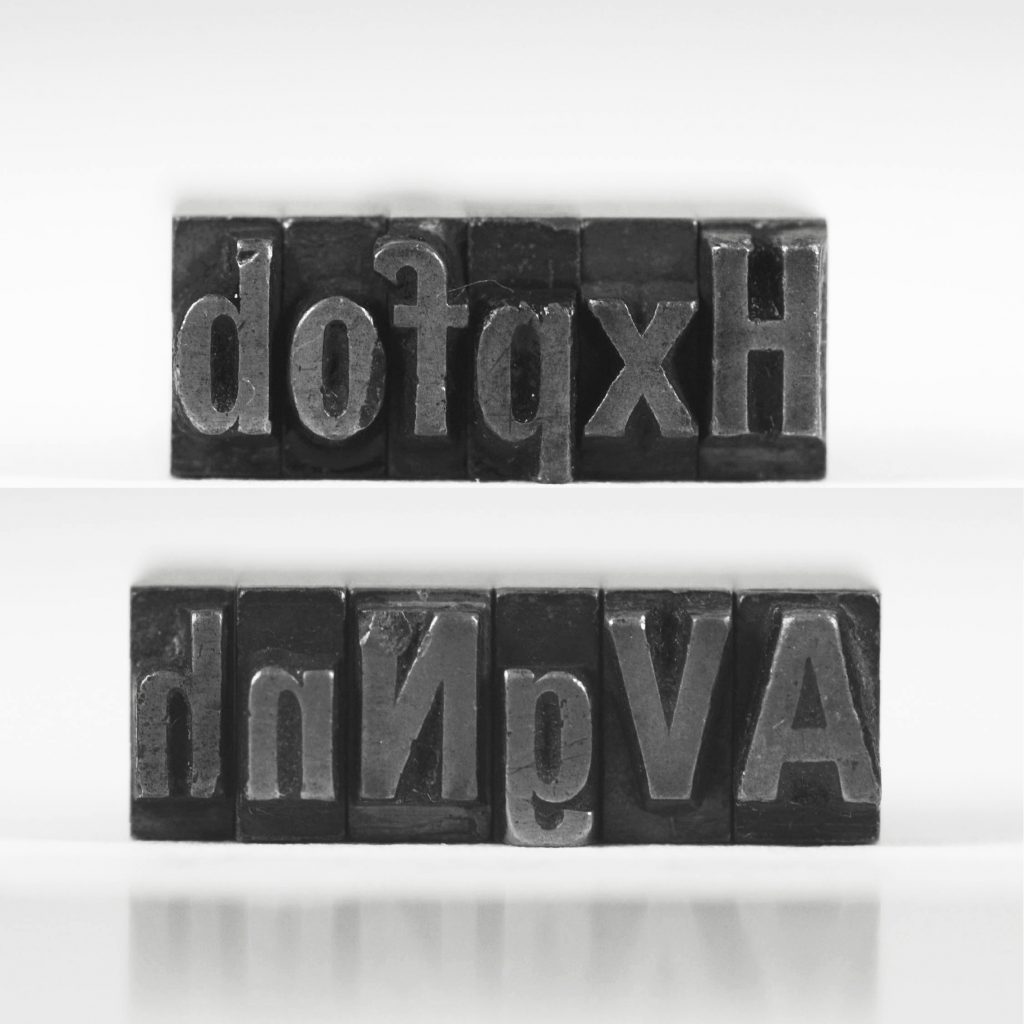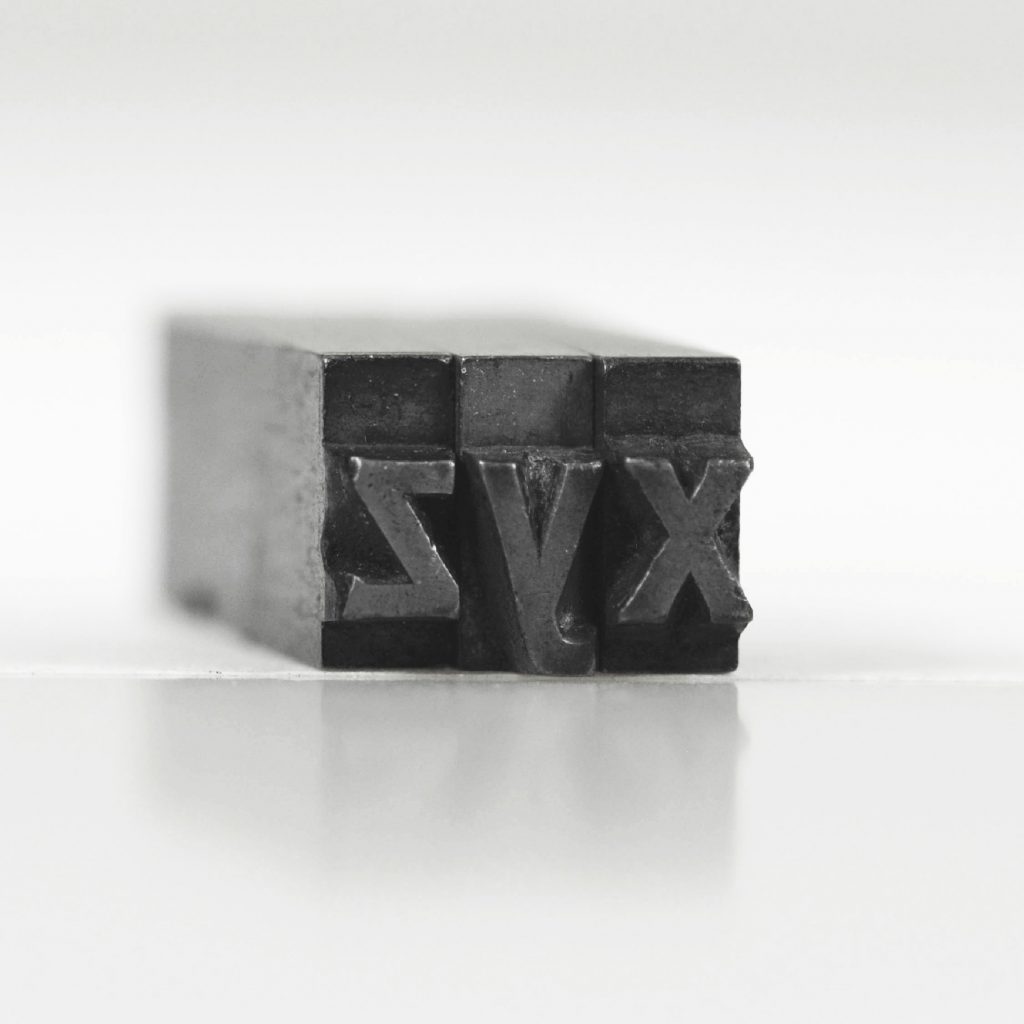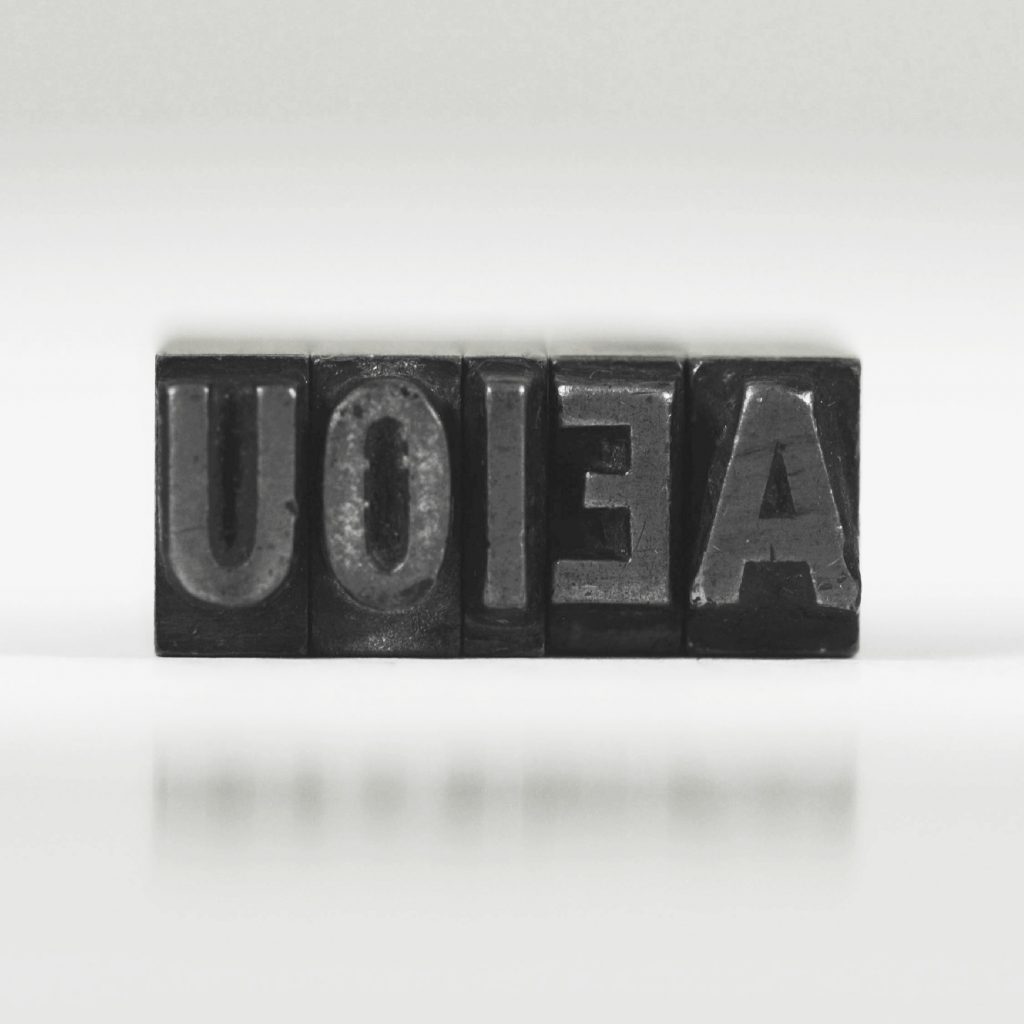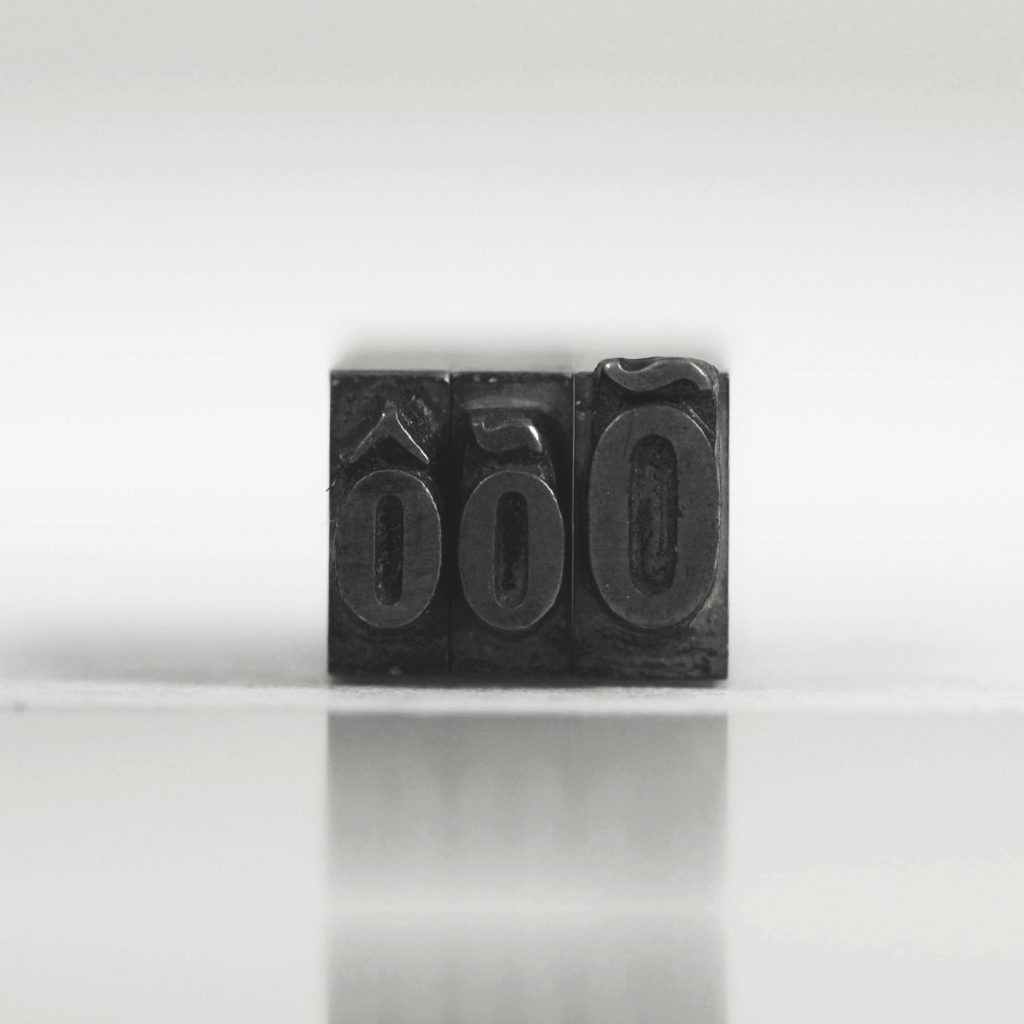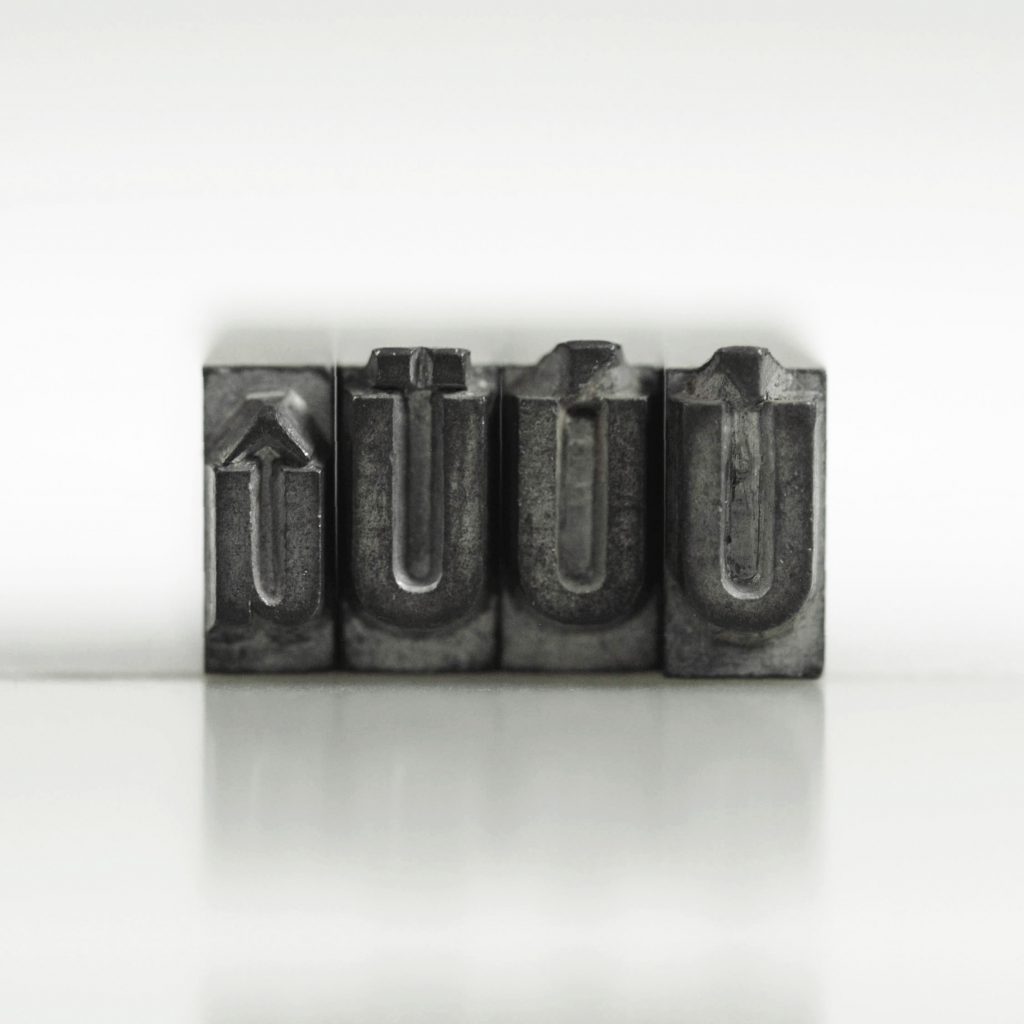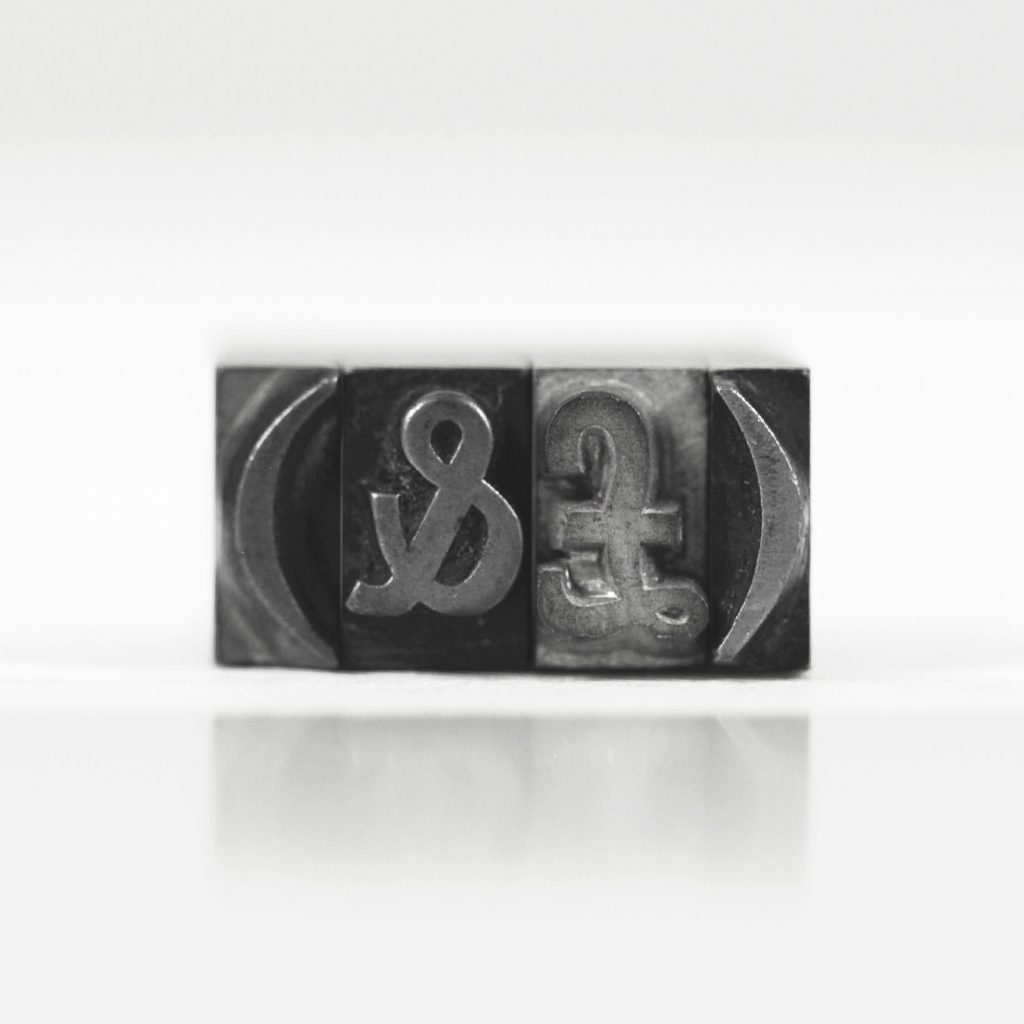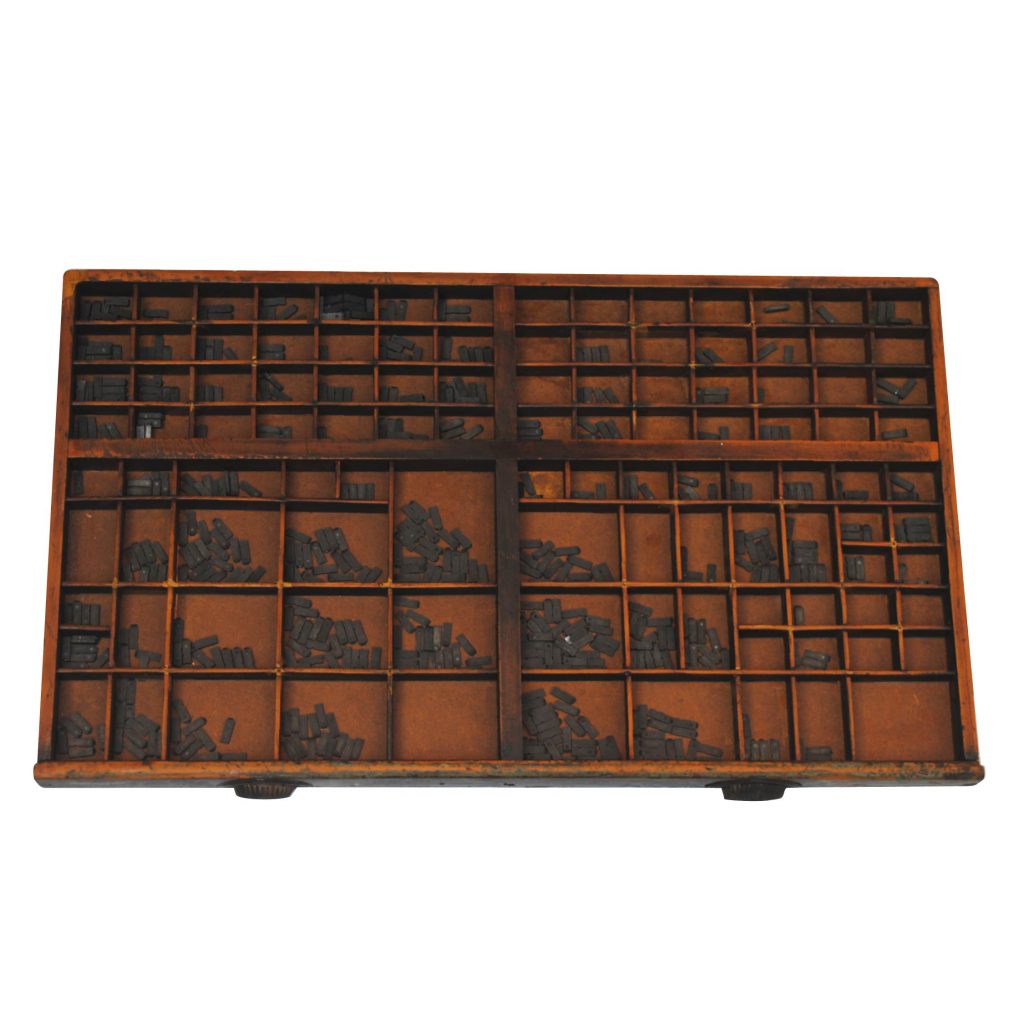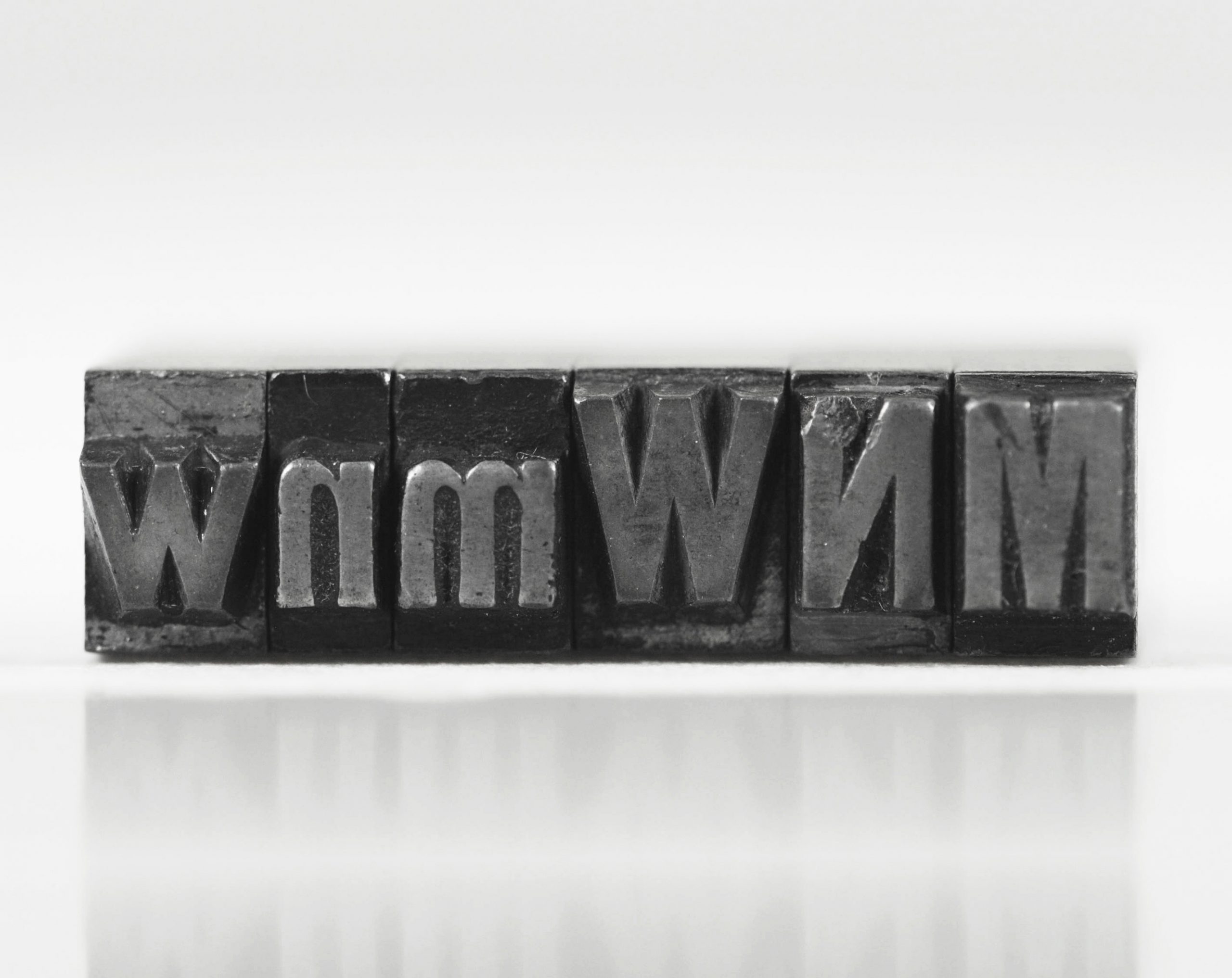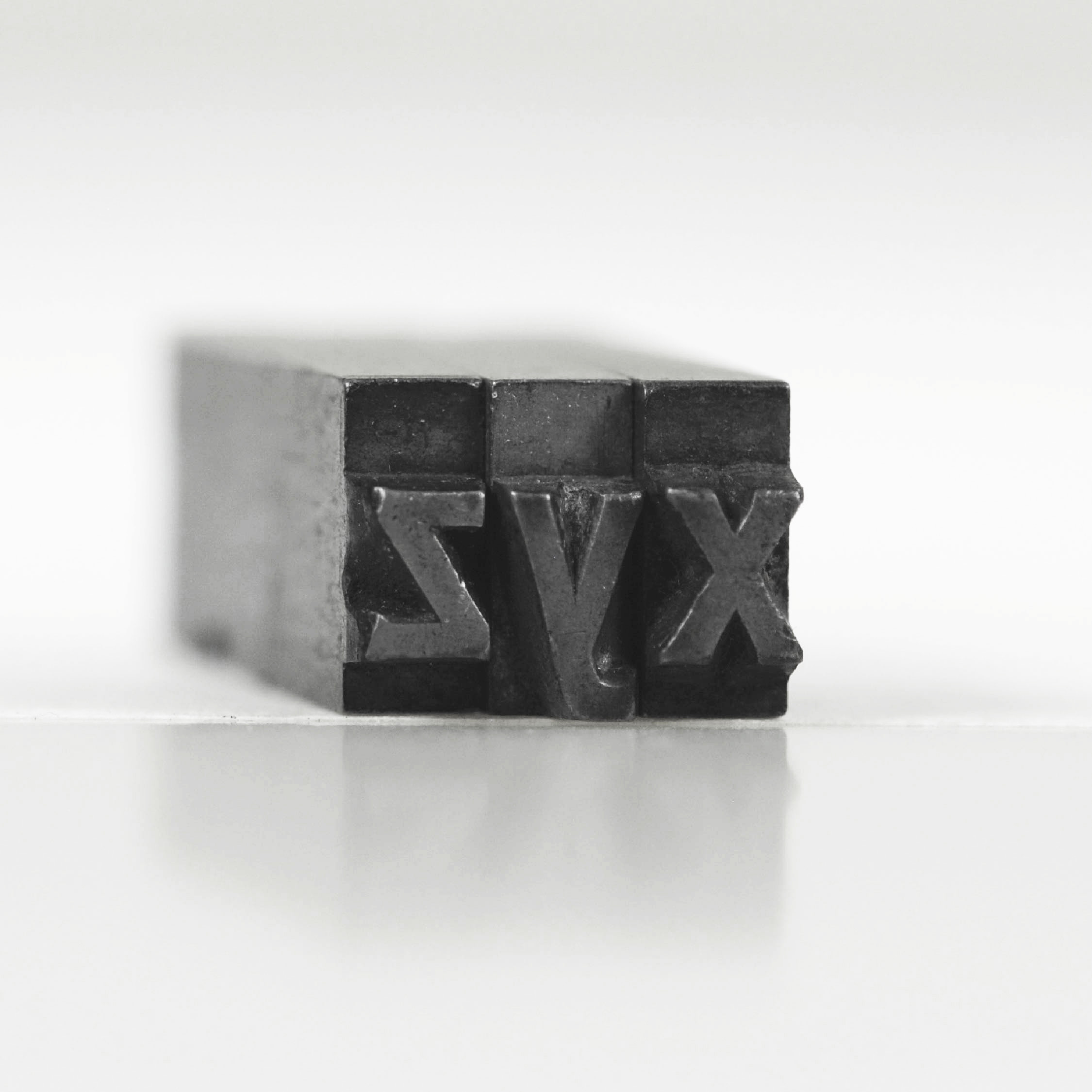
Steinschrift I 20pt
Grotesca
Acentos triangulares e pingos quadrados
Schelter & Giesecke
Schelter & Giesecke, Hauptprobe (v.1) [1912]
Marcas de uso recorrente; alguns tipos apresentam desgaste na face que pode comprometer a qualidade da impressão.
Maiúsculas | Minúsculas | Algumas maiúsculas acentuadas | Algumas minúsculas acentuadas | Numerais
Poucos tipos. Não é possível compor um texto extenso.
Foram encontradas duas fontes semelhantes presentes no catálogo de tipos da fundidora J.G. Schelter & Giesecke (1912), a Steinschrift I.
Garnitur e a Steinschrift II. Garnitur (também conhecidas apenas pelos nomes Steinschrift I. e Steinschrift II.).
Após análises, foi constatado que se trata da primeira opção. Segundo Wetzig (1926), essa fonte foi comercializada por diversas fundidoras de língua alemã com pequenas variações nos desenhos e nos nomes. O nome utilizado pela fundidora remete à “inscrição em pedra", em tradução livre, o que configura um descritivo de suas características.
A fonte inclui “ñ”, utilizado na escrita de idiomas como espanhol, quechua, tagalog, entre outros (Bringhurst, 2018, p. 348).